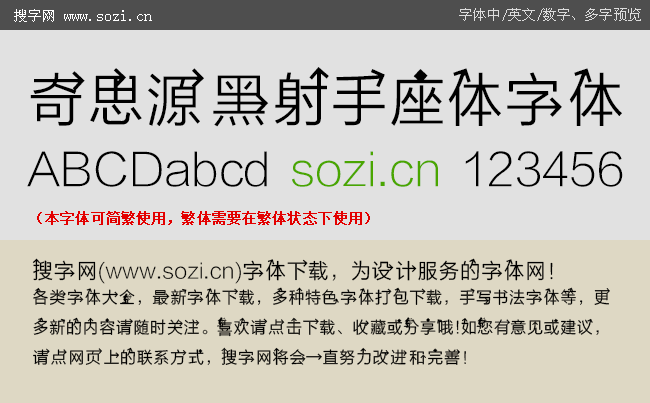
奇思源黑射手座體字體
搜字網(wǎng)給大家提供一款奇思源黑射手座體字體手機(jī)中文字體下載。這款手機(jī)字體是以黑體字體為原形,個(gè)別筆畫加上了箭頭圖案。具有黑體端正易認(rèn)的風(fēng)格,又很有趣味性,特別適合喜歡手機(jī)字體個(gè)性一些的朋友在手機(jī)上安裝使用。